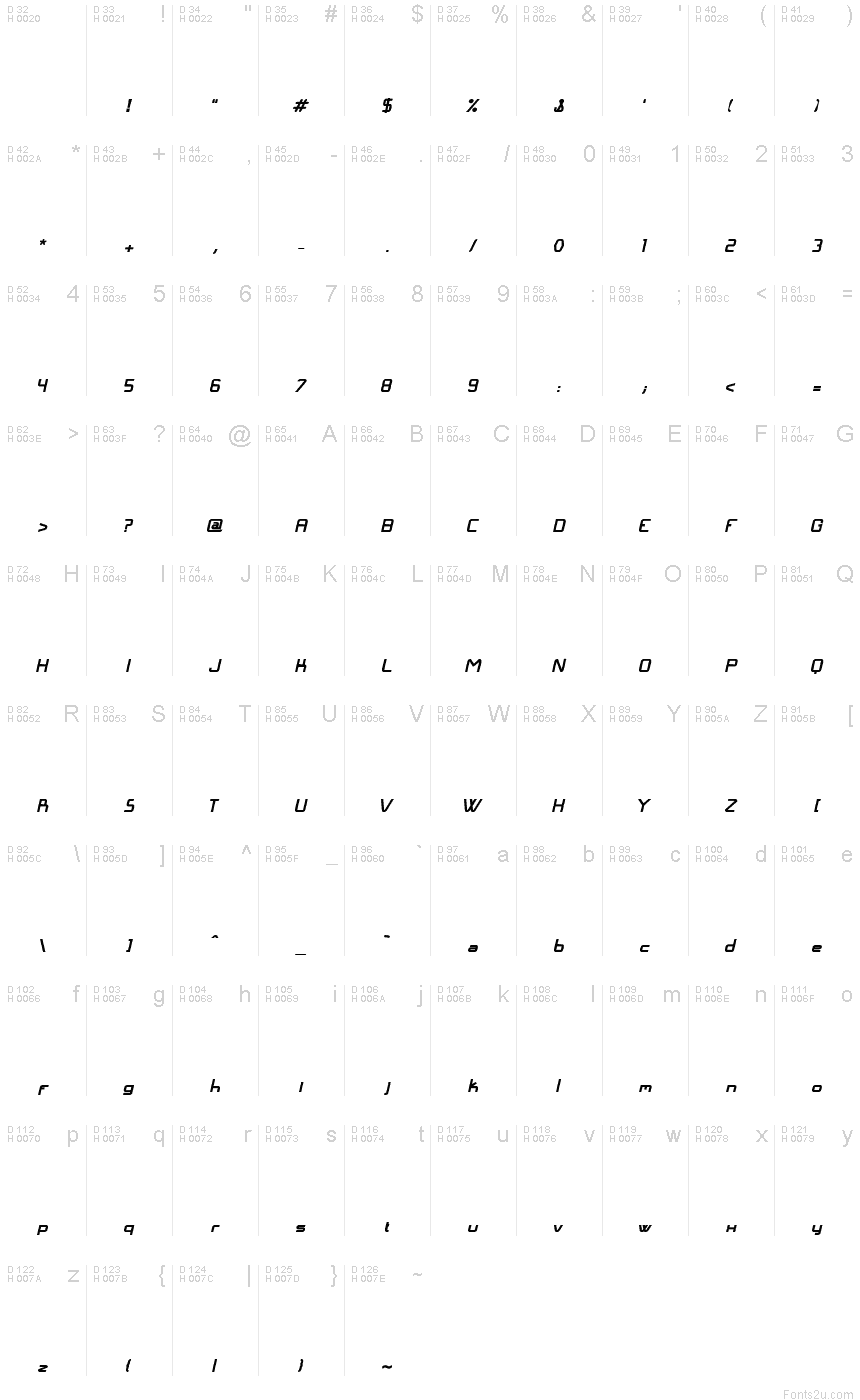
Langó BoldItalic
Langó Bold Italic è un font display gratuito con una struttura fortemente inclinata e curve arrotondate e troncate, che conferiscono al carattere un ritmo rapido, proiettato in avanti. I tratti pesanti sono rifiniti con angoli lisci, rendendo la forma complessiva compatta e funzionale piuttosto che decorativa.
Questo font gratuito è perfetto per titoli, loghi, poster, grafiche sportive, packaging e testi promozionali brevi in cui una forte presenza corsiva aiuta a trasmettere dinamismo. Langó Bold Italic è ideale anche per branding e title card perché le sue forme condensate e lineari rimangono incisive anche nelle grandi dimensioni, senza bisogno di ulteriori ornamenti.